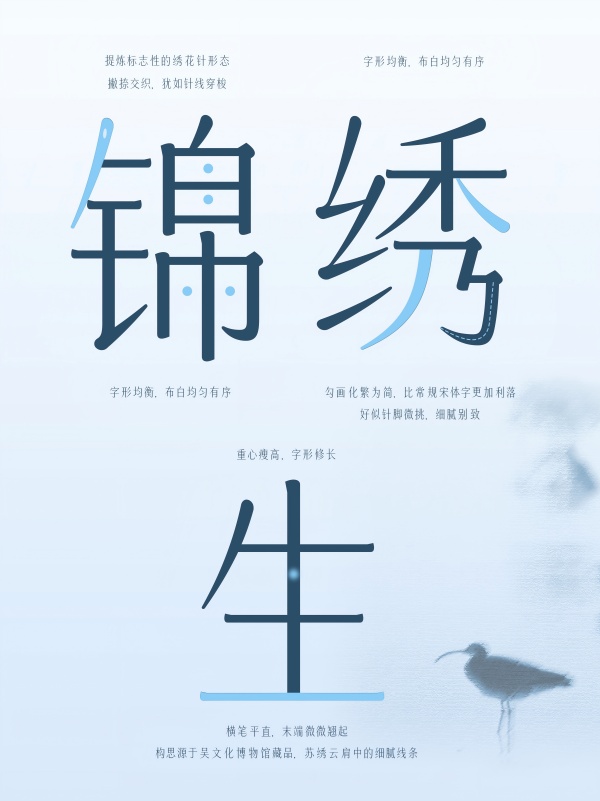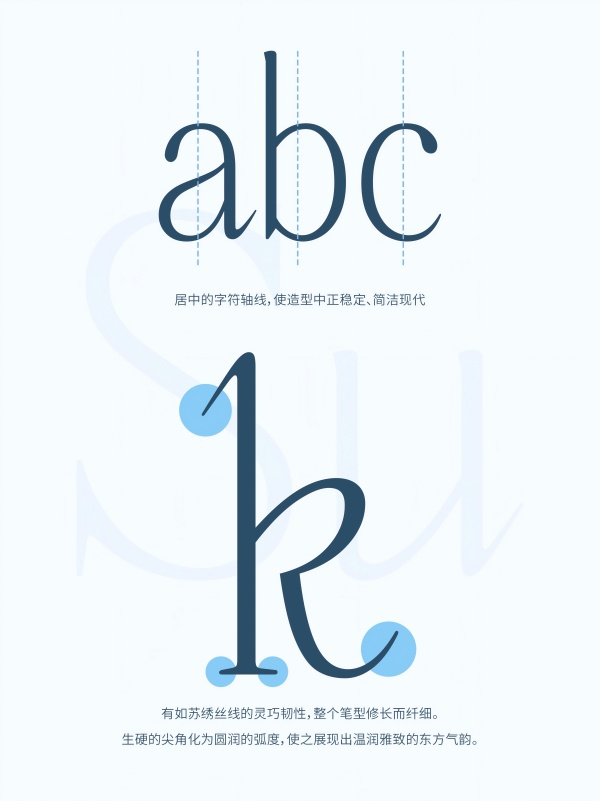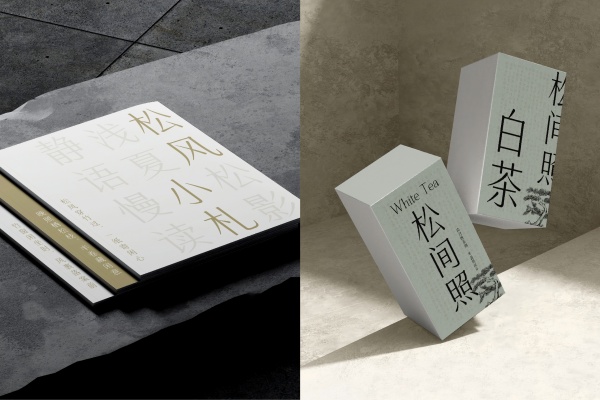
字魂创意字库×吴文化博物馆:非遗定制字体正式发布
字体,是品牌视觉的基石,深刻塑造着用户的感知与体验。随着越来越多的企业与品牌IP对强化形象传达、建立统一视觉资产的需求,定制字体已然成为品牌营销的新趋势。这次作为“吴中非遗IP”转化的首个项目,字魂创意字库从苏绣技艺中汲取灵感,将针尖上的匠心融入笔墨之间,为吴文化博物馆打造了一款非遗定制字体——“字魂吴文化博物馆苏绣体”。
苏绣,传承两千余年,冠绝中国四大名绣。一根丝线能劈至一百二八分之一细,一件精品苏绣需近百万针绣制,绣娘凝神屏意,日复一日,方得佳作天成。
细密针脚,含蕴着江南的温婉灵秀;流转丝线,珍藏有非遗的坚守传承。
字魂吴文化博物馆苏绣体,从苏绣非遗技艺中汲取灵感,将代表性的绣针造型融入笔画,让东方之美焕发于字里行间。字形刚柔并济,灵动秀雅,既似苏绣精品,温婉考究;又如江南女子,亭亭玉立。
字形的横笔中,还化用了吴文化博物馆藏的苏绣云肩——《四合如意》这一作品中的线条,使其横画笔直平整,但末端上翘,恰似绣娘用绣针挑线的动作,活灵活现。
西文字体部分也保留了 “绣花针” 的灵感 —— 在纤细的衬线体基础上,增加以手写痕迹,使西文字体更多一份温度与人文主义。。而字母尖角处设计成圆润且利落的线条弧度,使这款定制字体的西文也能展现出独特的东方气韵。
在当下激烈的市场竞争中,品牌越来越注重文化叙事。而非遗技艺中蕴含的独特美学、精湛技艺和匠心精神,能够带来一臂之力。
「字魂吴文化博物馆苏绣体」按国家字库标准GB2312-7144进行制作,包含7144个中文、字母、符号和数字。作为一款新中式的字体设计作品,既有着源于传统的温润雅致,也有着现代审美所需求的简洁利落。在商业使用中,可以被广泛应用于各个行业和场景。
在文化旅游产业,酒店、景区等可以使用该字体制作宣传海报、周边产品等,为游客营造浓厚的文化氛围,提升旅游体验;在时尚潮流领域,服饰、美妆等品牌可以将字体应用于产品标签、广告宣传和产品包装中,展现独特的视觉审美与文化魅力。「字魂吴文化博物馆苏绣体」将在赋能吴文化博物馆运营与文化双场景的同时,让更多的企业与品牌可以在跨界字体应用中获得新的商业势能。字魂创意字库也希望透过字体,为用户、行业和社会创造更多价值与美好。